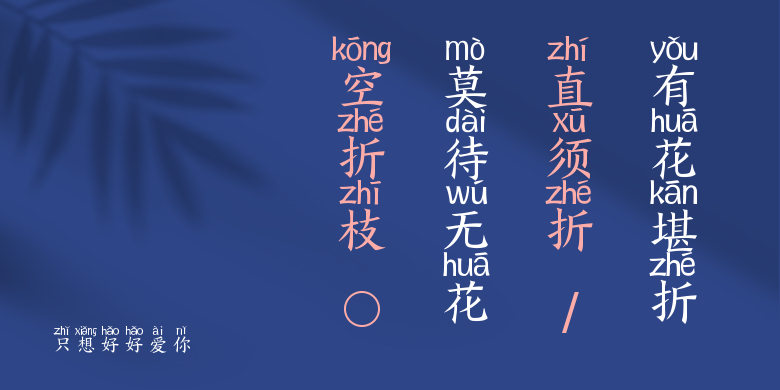
只想好好爱你
只想好好爱你,这款字体结构工整、笔画清晰,兼顾美观与易读性,适用于标题、正文、海报、包装、LOGO 等多种场景。字形优雅稳定,风格百搭耐看,适配日常排版与创意设计,让文字呈现更舒适、更具质感。只想好好爱你一笔一画,皆是细节,以均衡的比例、流畅的线条打造舒适视觉体验,字形端正大气,风格简约现代。无论是商业设计、品牌宣传还是日常排版,都能轻松驾驭,让文字更有格调与力量。只想好好爱你字体下载。